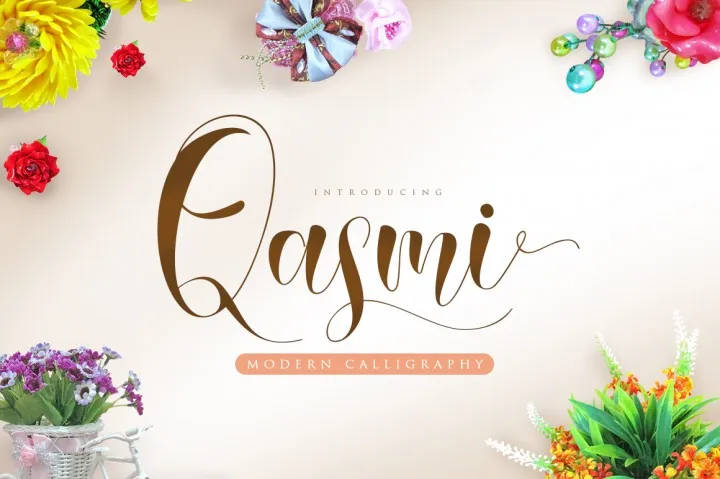
Qasmi Script Font – Download Grátis
A Qasmi Script Font é uma elegante escolha para quem busca trazer um toque delicado a qualquer projeto visual. Introduzida pelo designer Hamilton, essa tipografia script moderna e fresca é perfeita tanto para criações de logotipos quanto para projetos de marca, convites ou cartas de cumprimento. Ela se destaca por sua aparência natural e aparente manualidade, tornando-a ideal para a criação de posters e qualquer tipo de projeto gráfico que você possa estar desenvolvendo. Seja o próximo projeto da sua lista, certifique-se de incluir um detalhe único e artesanal com Qasmi Script Font.